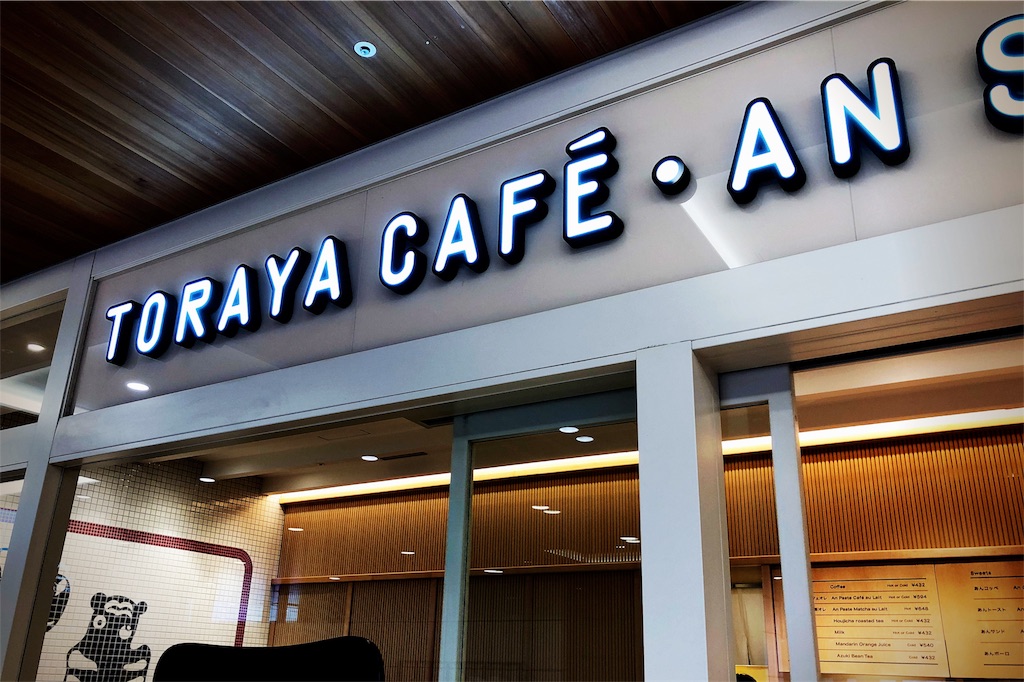
TORAYA CAFE・AN STAND / トラヤカフェ・あんスタンド
私は餡が好きである。
餡パンに牛乳こそ最強のスタイルと信じて疑わない私は新宿にあるTORAYA CAFEがずっと気になっていた。そこで、暮れも押し迫った時期にTORAYA CAFEに初訪問した。
TORAYA CAFEは京都で生まれ、5世紀にわたって和菓子屋を営んできた「とらや」がつくったカフェ。自由で新しいお菓子の世界の提案をコンセプトに「とらや」のあんを使った、とらやがつくるもうひとつのお菓子を届けることをコンセプトにしている。
とらやは室町時代に京都で創業し、後陽成天皇に和菓子を献上して以降、皇室御用達の製菓業となり、これまで約480年の歴史を持ち、明治時代になって東京に移った。特に羊羹が有名で「とらやの羊羹」として広くその名を知られている。
今回はそのTORAYA CAFE・AN STANDの新宿店へと訪問した。
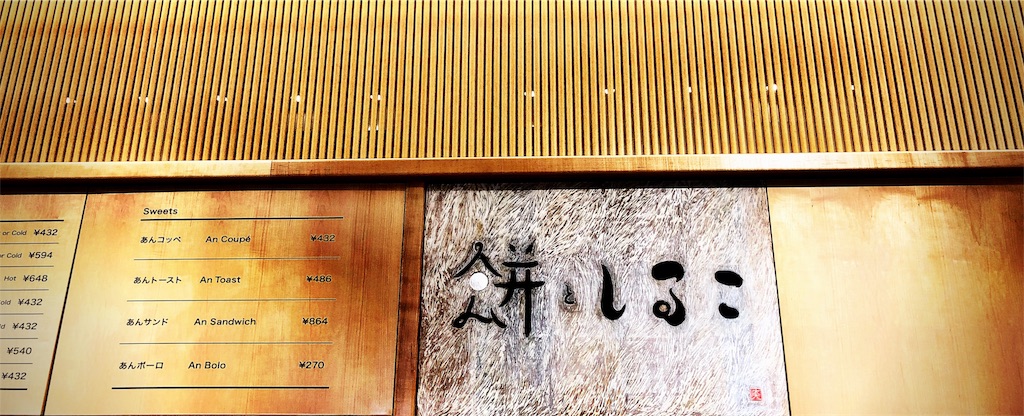
餅としるこの文字、お正月に良さそう。
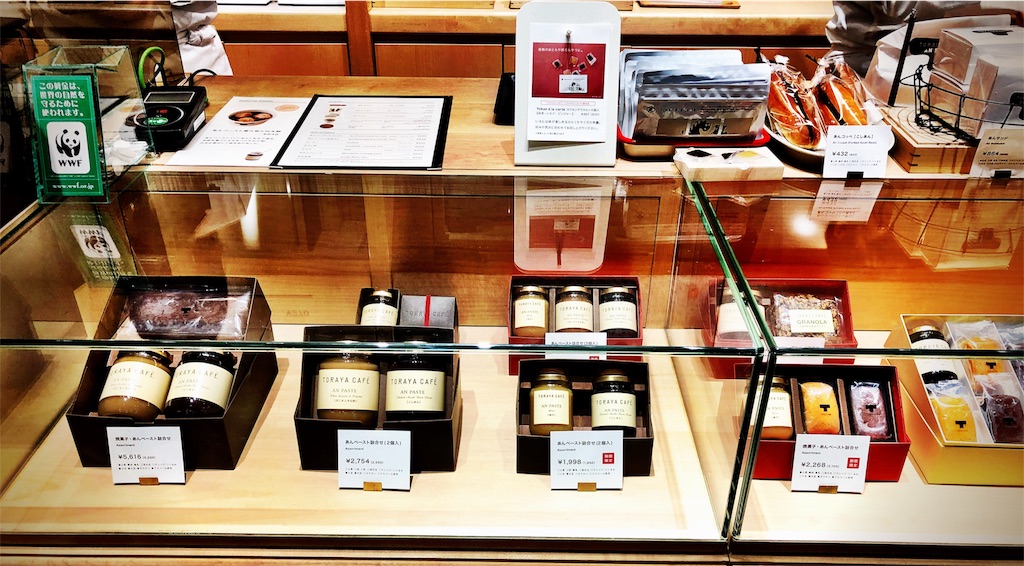
店内であんペーストなどを販売しているほか、店内併設のカフェであんこっぺなどが食べれる。
あんコッペ[こしあん]
ヤマザキパンのつぶあん&マーガリンが好きな私はテイクアウトで「あんコッペ[こしあん]」を注文。
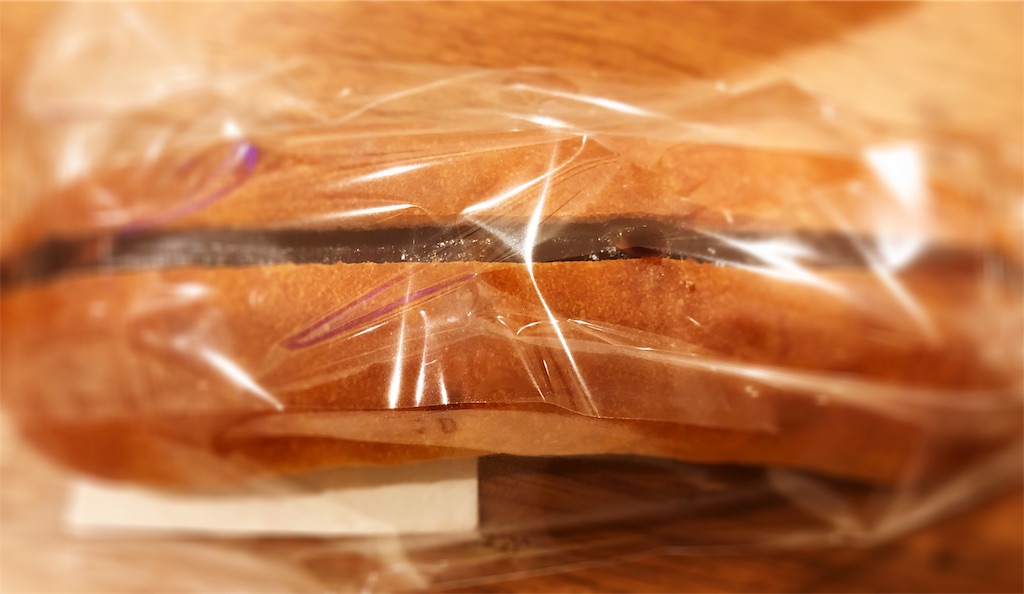
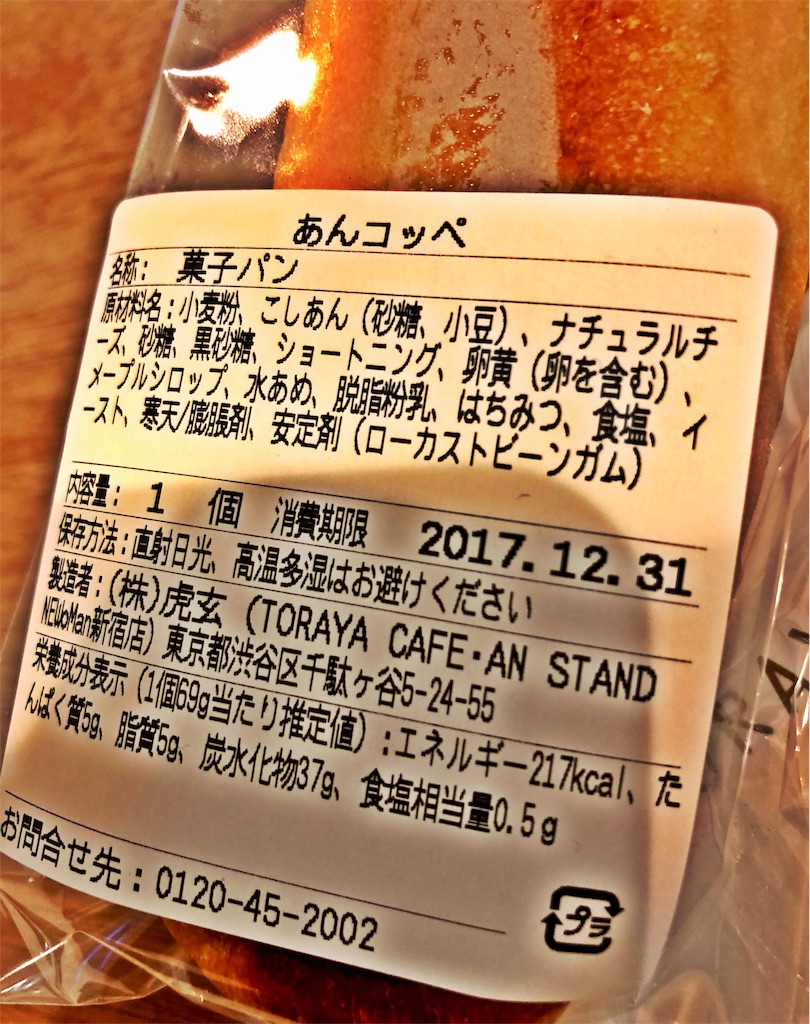
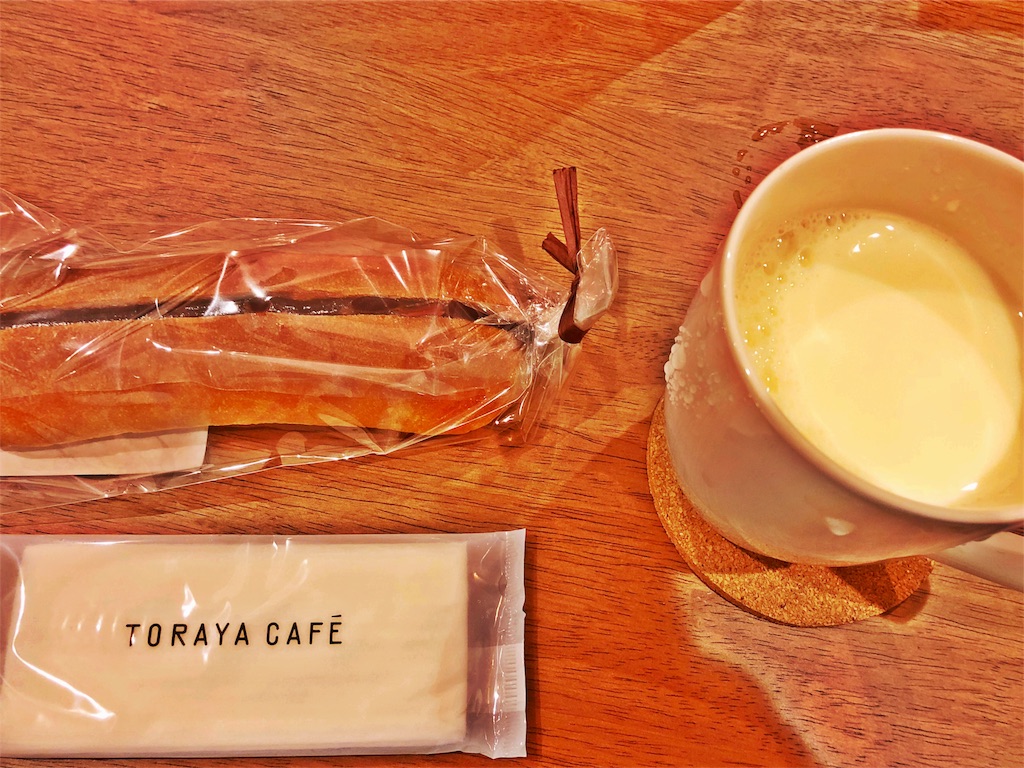
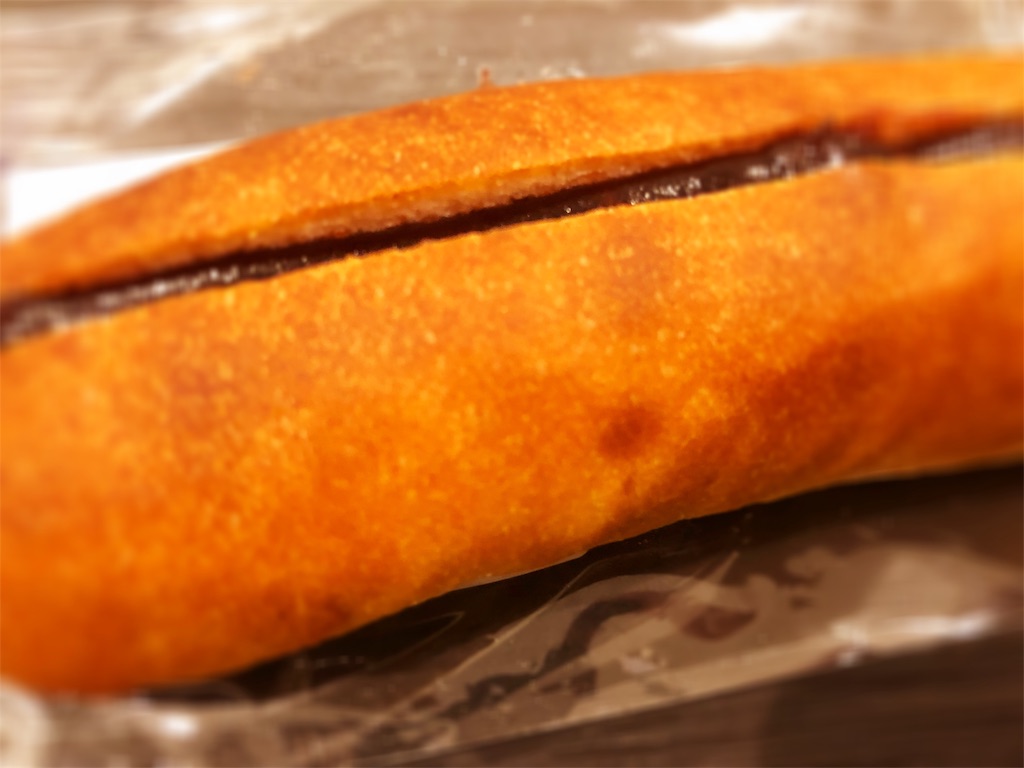
もちろん牛乳を相棒にいただいた。